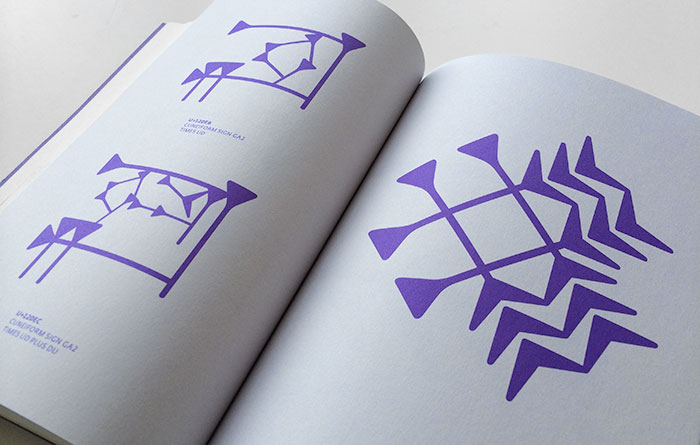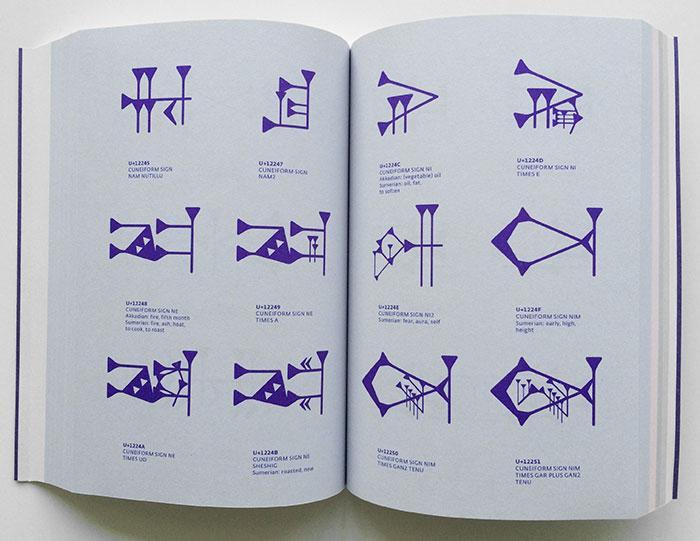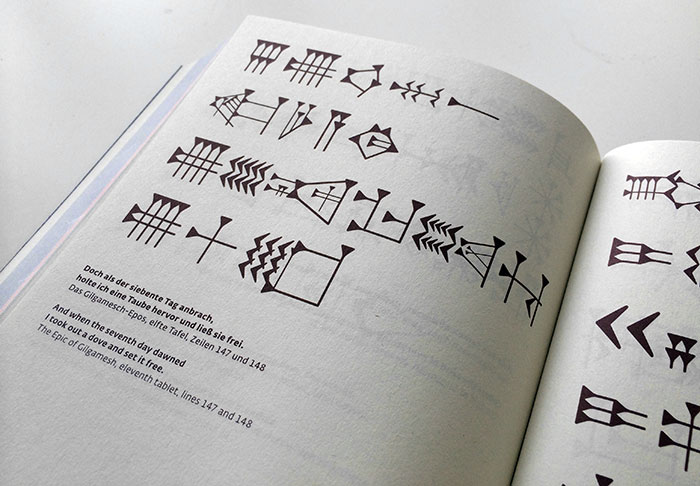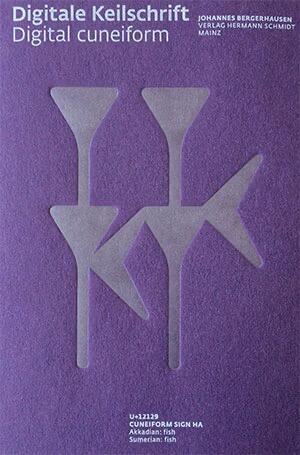
Das Projekt decodeunicode der Fachhochschule Mainz bietet einen Zugang zu den (Unicode-)kodierten Schriftzeichen der Welt. Für die Website fehlte jedoch zunächst ein adäquater Font zur Darstellung aller Keilschriftzeichen. Mit der Schrift DecodeCuneiform wurde dieser schließlich geschaffen. Ein Projekt, dass es mit über 1000 teils recht komplexen Glyphen in sich hatte und sieben Jahre Entwicklungszeit benötigte.
Die Schrift wurde 2013 fertiggestellt und das Buch Digitale Keilschrift ist sozusagen das vollständige Schriftmusterbuch der Schrift. Das Werk funktioniert dabei wie ein Ableger des Decodeunicode-Buches. Zunächst wird auf knapp 100 Seiten die Geschichte der Keilschrift beleuchtet. Den größten Teil des 544 Seiten starken Buches machen dann die Glyphendarstellungen aller Keilschriftzeichen im Unicode aus. Am Ende gibt es dann noch Satzbeispiele der Schrift anzuschauen.
Das Buch ist zweisprachig in deutsch und englisch gesetzt. Eine Lizenz zur privaten Nutzung des Keilschrift-Fonts von Johannes Bergerhausen, Andrea Krause und Stefan Pott ist im Kaufpreis des Buches enthalten.